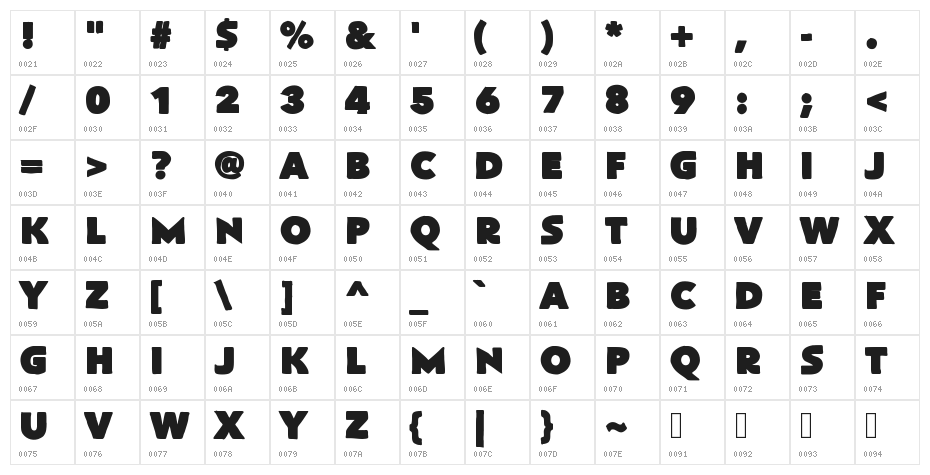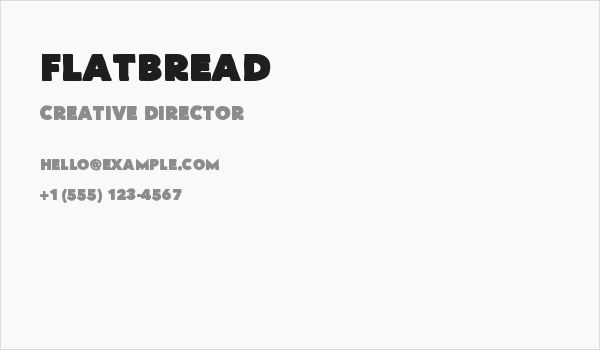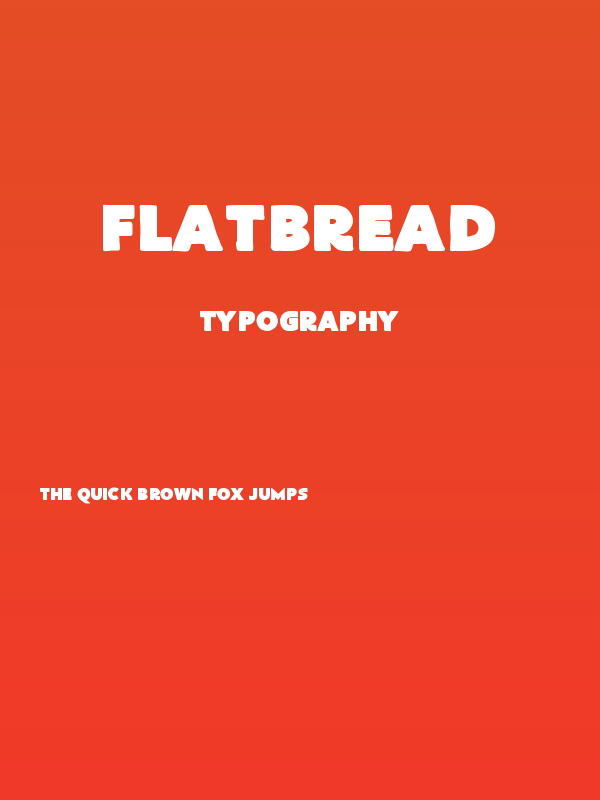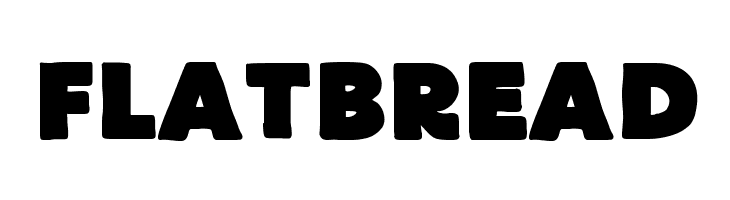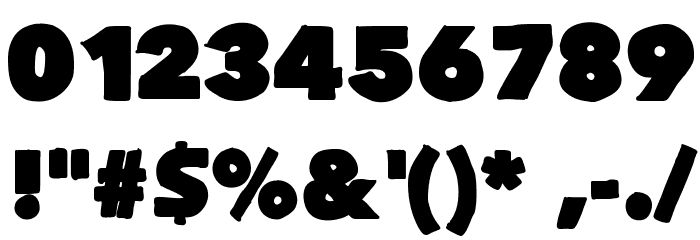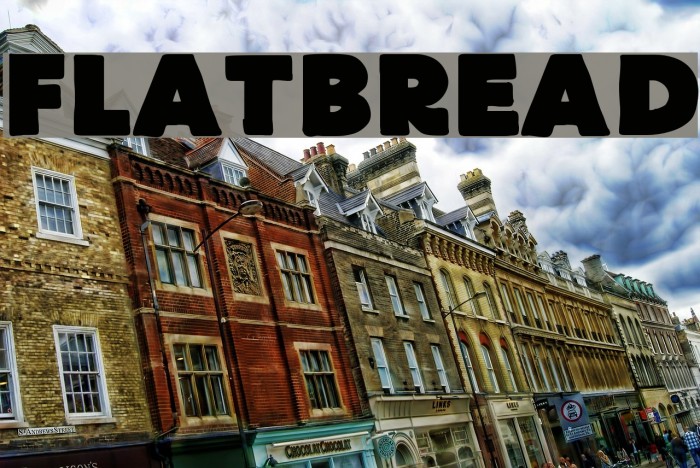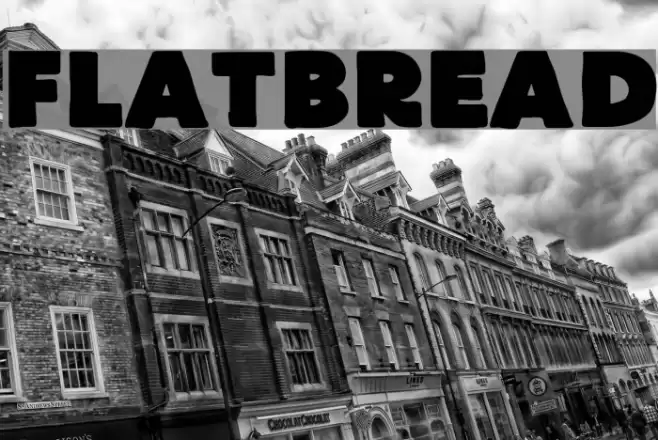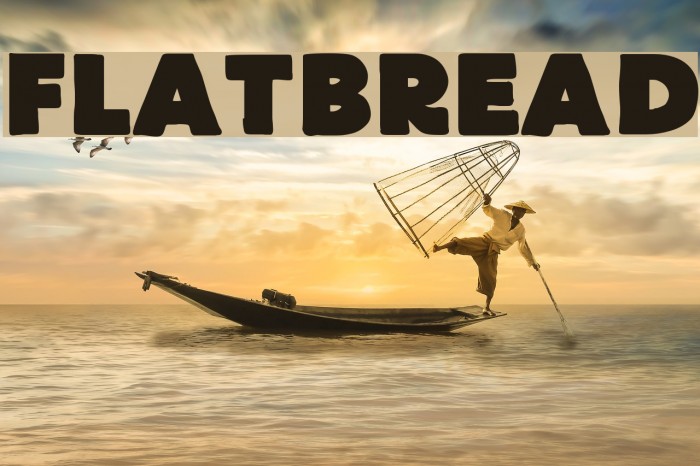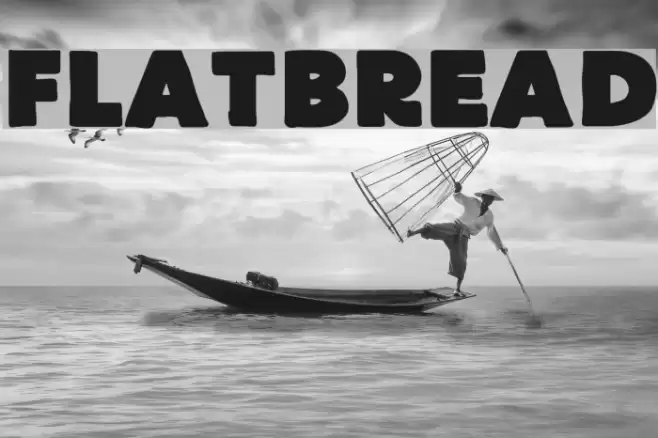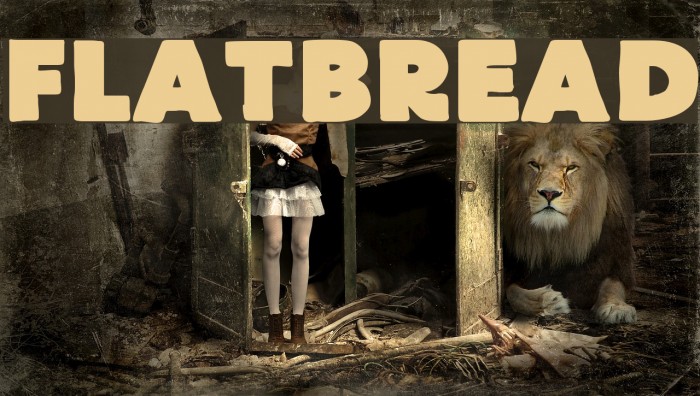
FlatBread Font
| Stil general | Playful, Cartoonish |
| Caz de utilizare | Headlines, Posters, Branding |
| Proiecte propuse | Ideal for children's books, playful branding, posters, and any design needing a fun and bold typeface. |